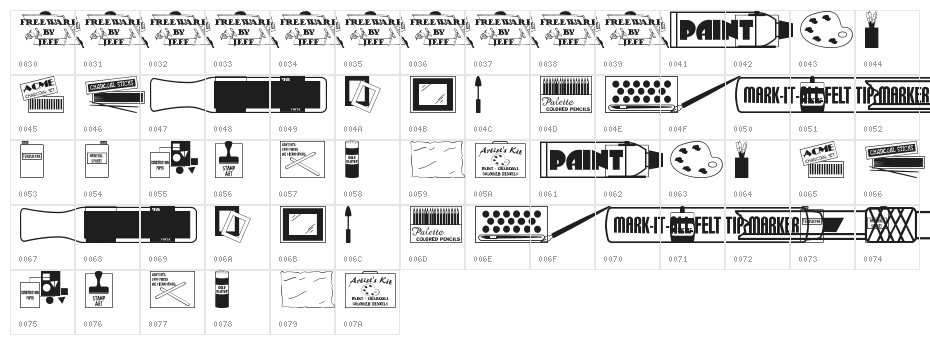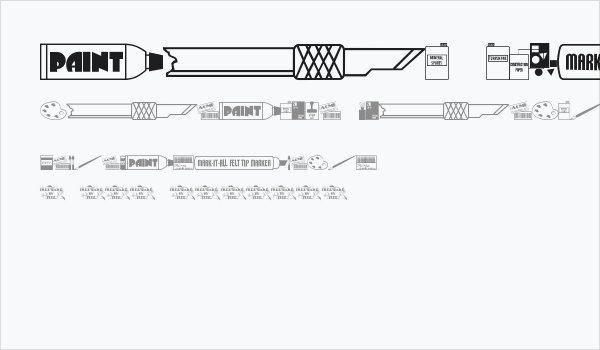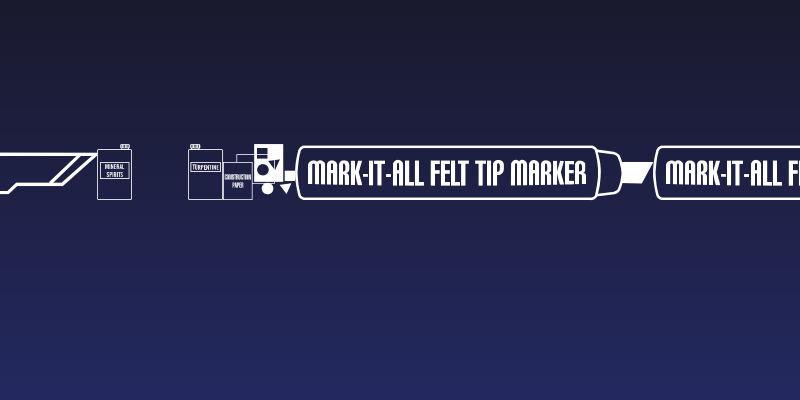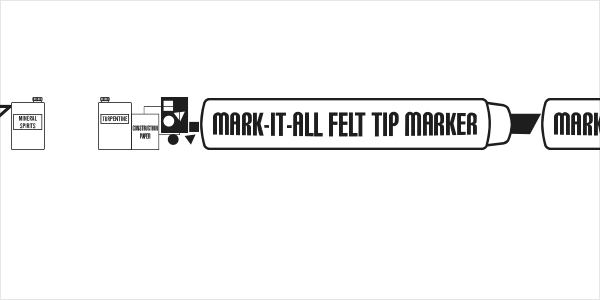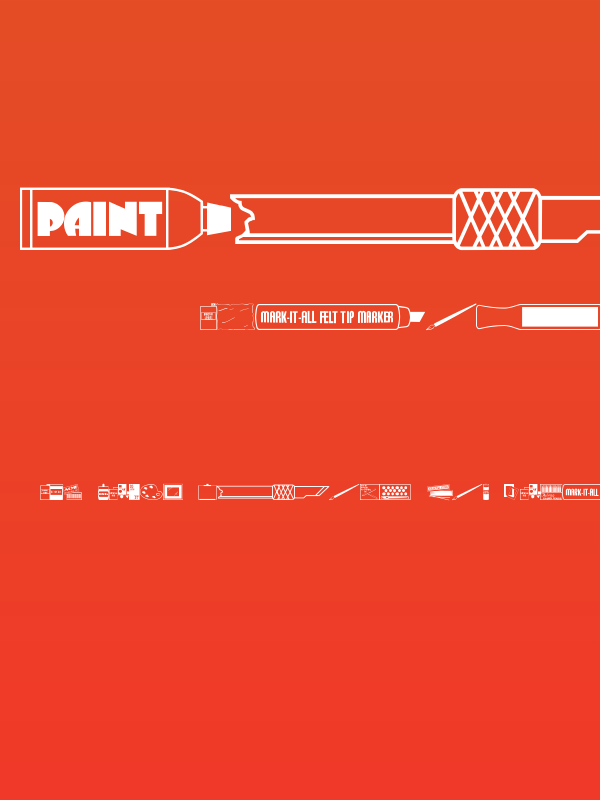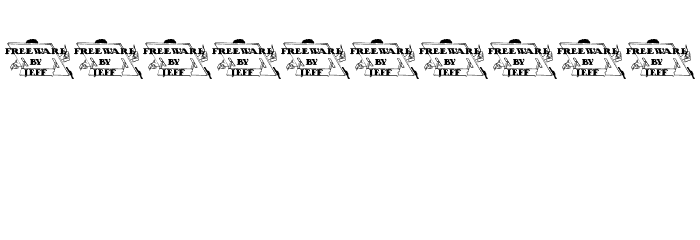
Art Supplies JL Font
| Caso d'uso | Decorative borders, artistic projects, educational materials. |
| Progetti proposti | Ideal for use in artistic projects, educational materials about art, or as a decorative border in creative designs. |